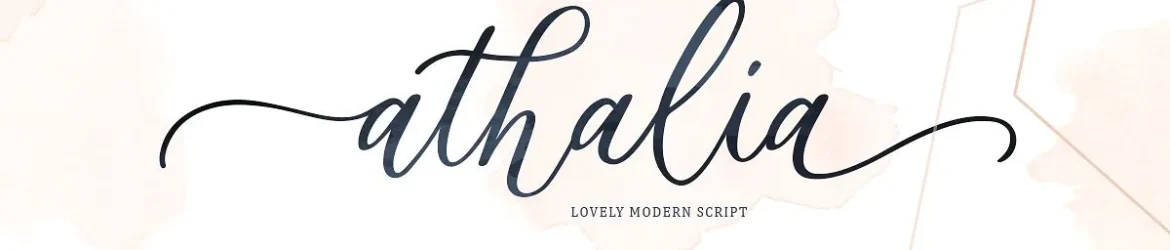
Athalia Script Font é uma elegante tipografia script que combina sofisticação simples com uma delicada textura artística. Ideal para dar um toque tradicional e luxuoso a qualquer projeto, esta fonte moderna de escrita manuscrita é perfeita tanto para headlines quanto para logotipos, roupas, convites, marcações, embalagens, publicidade e muito mais. Com todas as letras maiúsculas e minúsculas, símbolos e números, set alternativo estilizado e ligaturas incorporadas, esta fonte é uma escolha versátil para designers buscando um estilo único que ressoa com conforto pessoal e elegância moderna. Seja você criando roupas de luxo ou design de ambientes, o Athalia Script Font pode transformar sua arte em algo ainda mais especial e memorável.